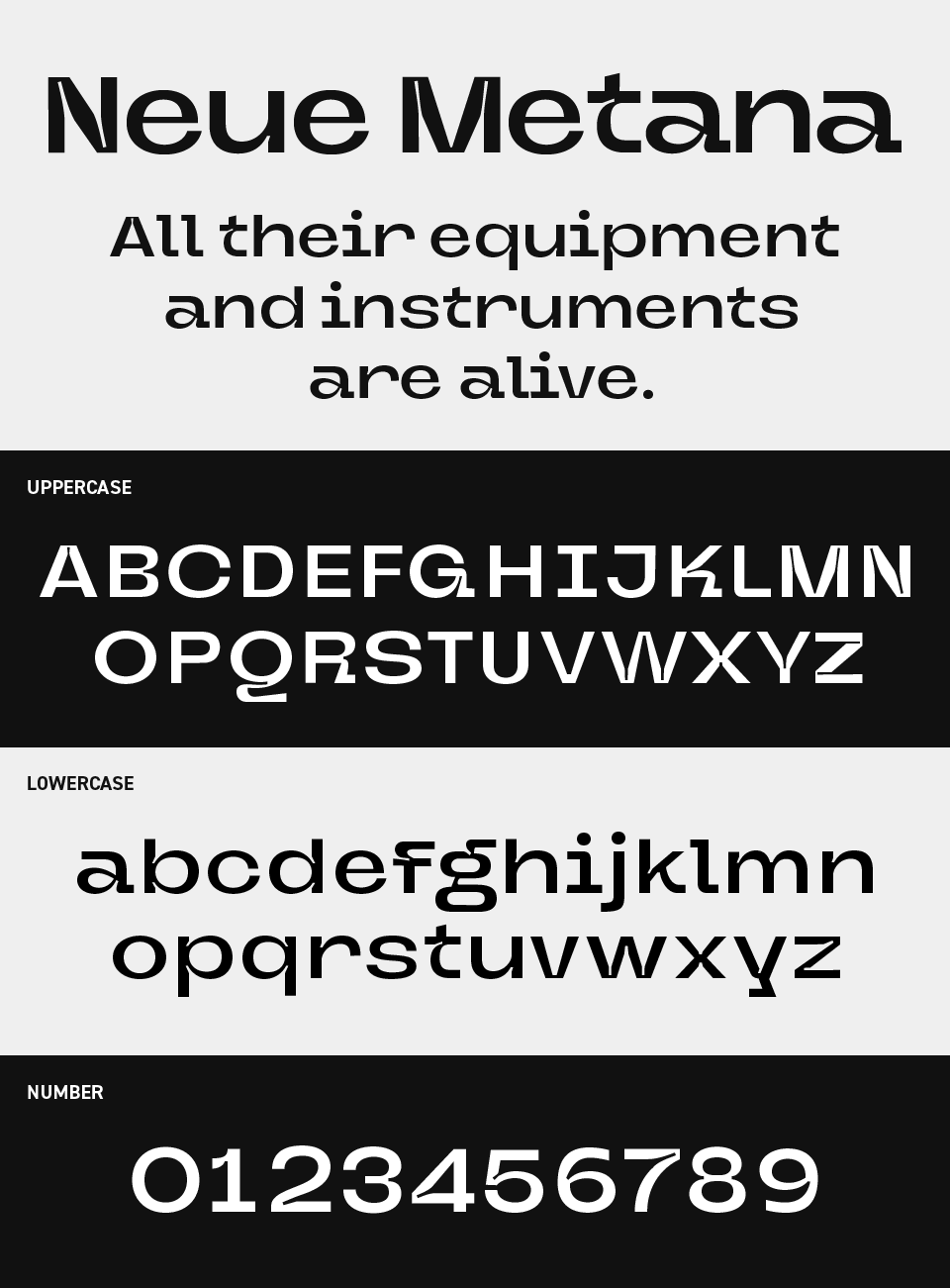
Neue Metanaフォントは、ジオメトリックな整った骨格に、シュッと切り込みが入っている遊び心のあるユニークなサンセリフ体です。
ロボット感やクラシカルと未来感が混ざったような、不思議とクセになる表情が魅力。
どこか理系っぽい印象もありつつ、文字ひとつひとつが柔らかく、キャッチーで軽やか。グラフィックの中でワンポイントとして使っても映える、アクセントになるフォントです。